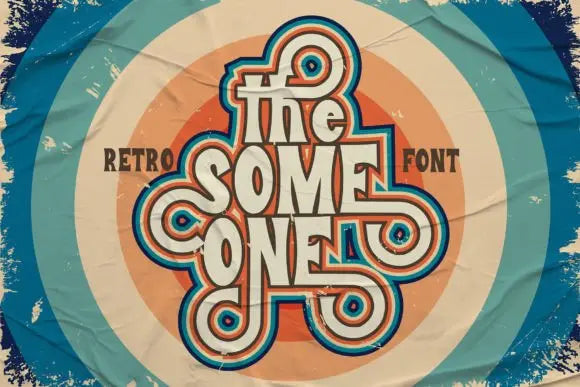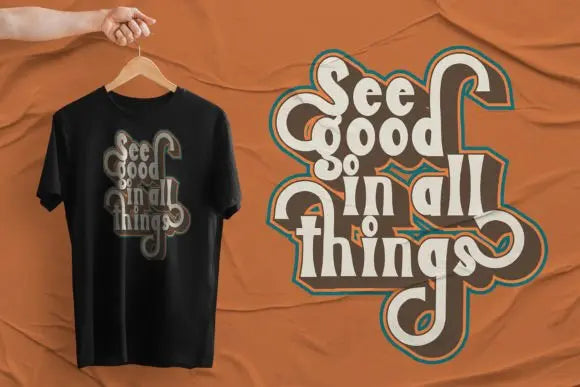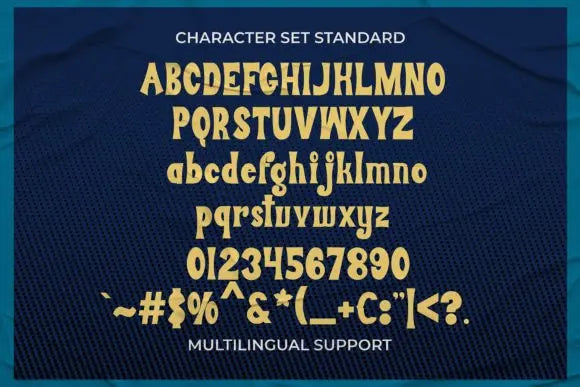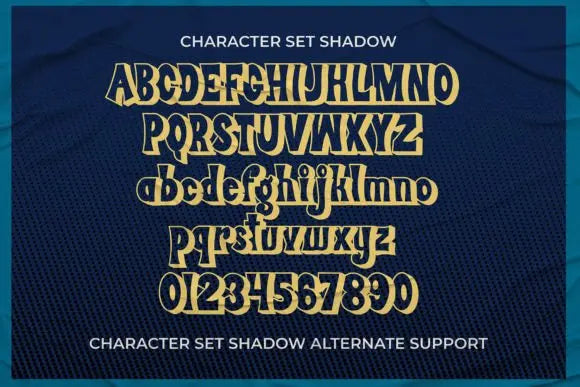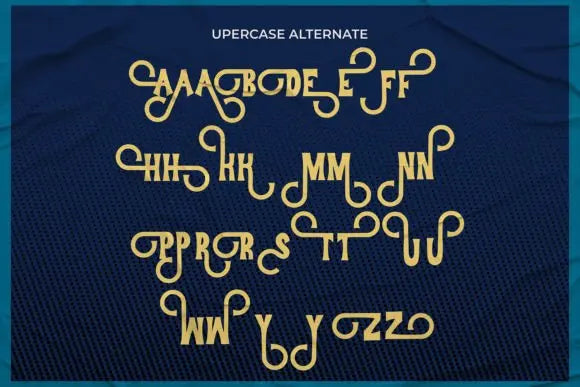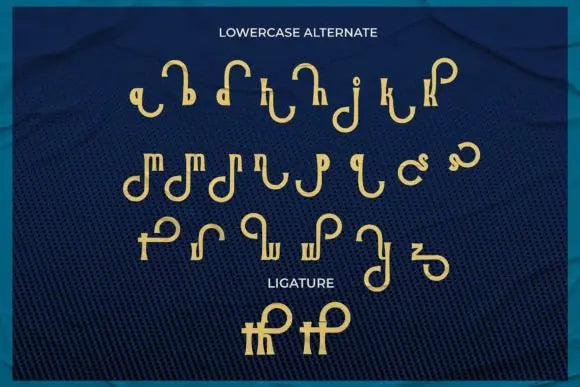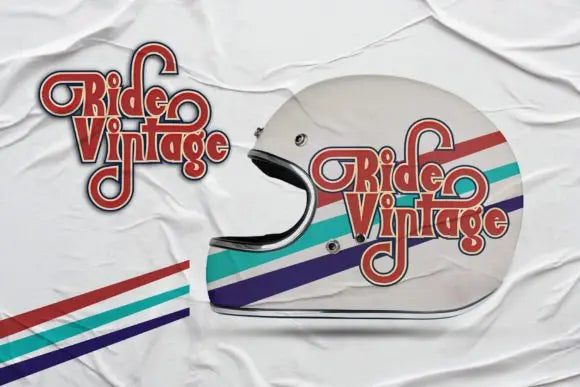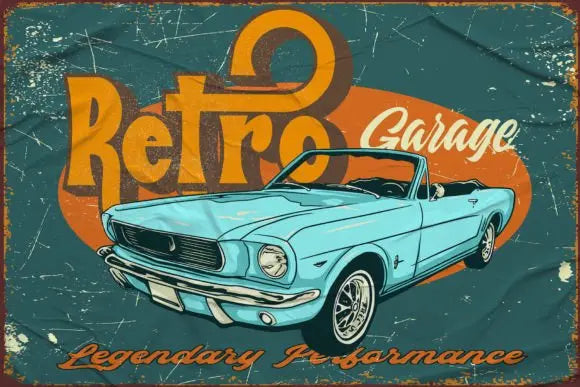
La fuente Some One
“The Some One” es una fuente de visualización con un tema retro, que presenta varios estilos alternativos que pueden ayudar a realzar sus diseños. Es ideal para una amplia gama de proyectos de diseño, como calcomanías para automóviles, diseños de camisetas o logotipos para marcas con temática retro.
Con su apariencia única y elegante, “The Some One” añade un toque de nostalgia y sofisticación a tus diseños.